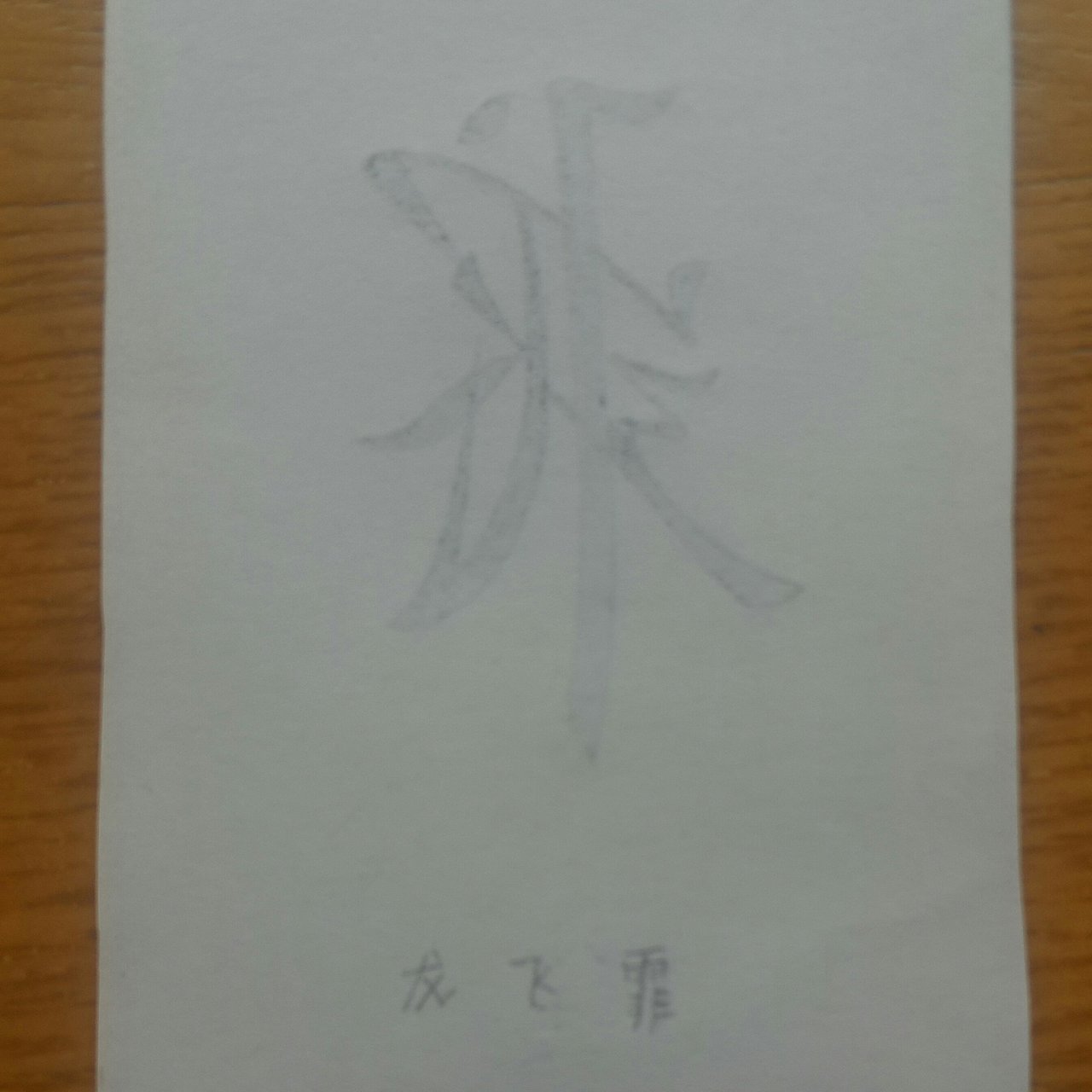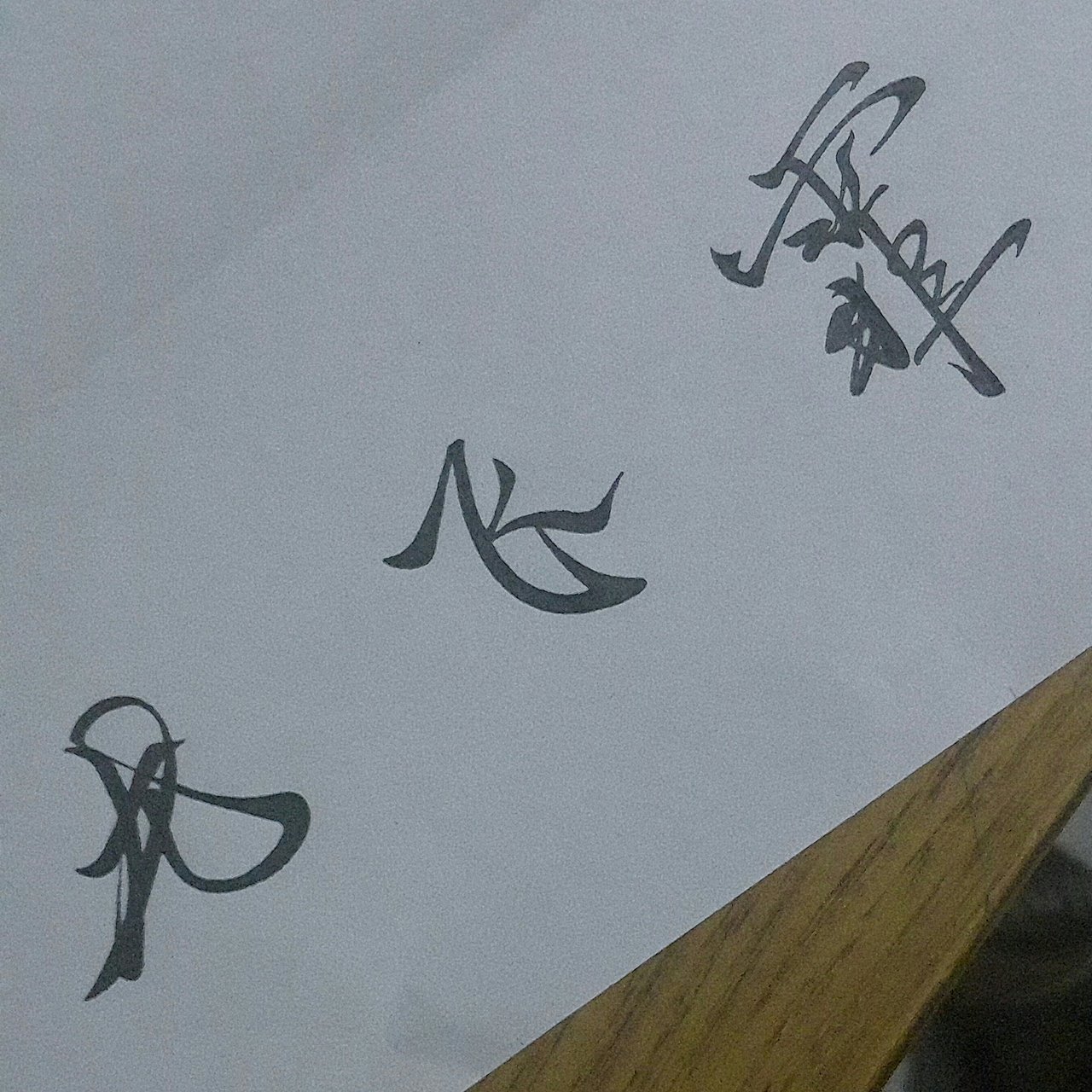
龙飞霏&字符
出于一种对文字线条艺术的热爱,针对人的名字及其字形特点,对字体进行了个人全新的设计,二次再造字,在中华字典库中找不到的,使其成为名字所有者的个人专有字符,具有一定代表性。
附带造字解释图片。
附带对应名字的毛笔字体设计。
再造字及读音
再造字所归属名字及其反面
造字过程及解字
再造字归属姓名毛笔1
再造字归属姓名毛笔2